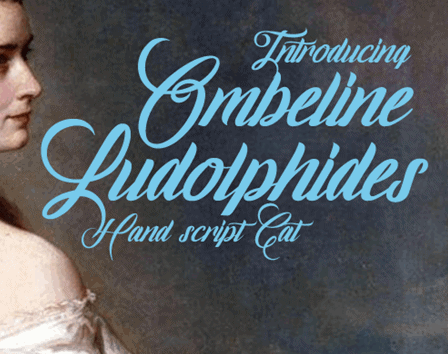
Ombeline Ludolphides Font – Download Grátis
Aqui está uma descrição envolvente para a página de download da font ‘Ombeline Ludolphides Font’, focada no estilo de calligrafia: A font ‘Ombeline Ludolphides’ é um trabalho de arte que combina elegância e versatilidade, perfeitamente adaptável tanto para letras cursivas quanto para formatos formais. Inspirado em garranchos livres e letras serifadas, esta fonte foi cuidadosamente criada por Cat Butcher. Ideal para designers aficionados ou profissionais que buscam uma opção única para seus projetos de arte. Ombeline Ludolphides está disponível gratuitamente para uso pessoal, mas com direitos autorais limitados para usos comerciais. Assim que confirmado o pedido comercial, os clientes podem usar a fonte sem preocupações adicionais. Cat Butcher respeita as leis e os direitos de propriedade intelectual, não permitindo que seu trabalho seja usado em conteúdos sexuais. Para mais informações ou para receber uma versão completa da font, é só entrar em contato com o designer. Estamos aqui para ajudar você a transformar sua arte digital!